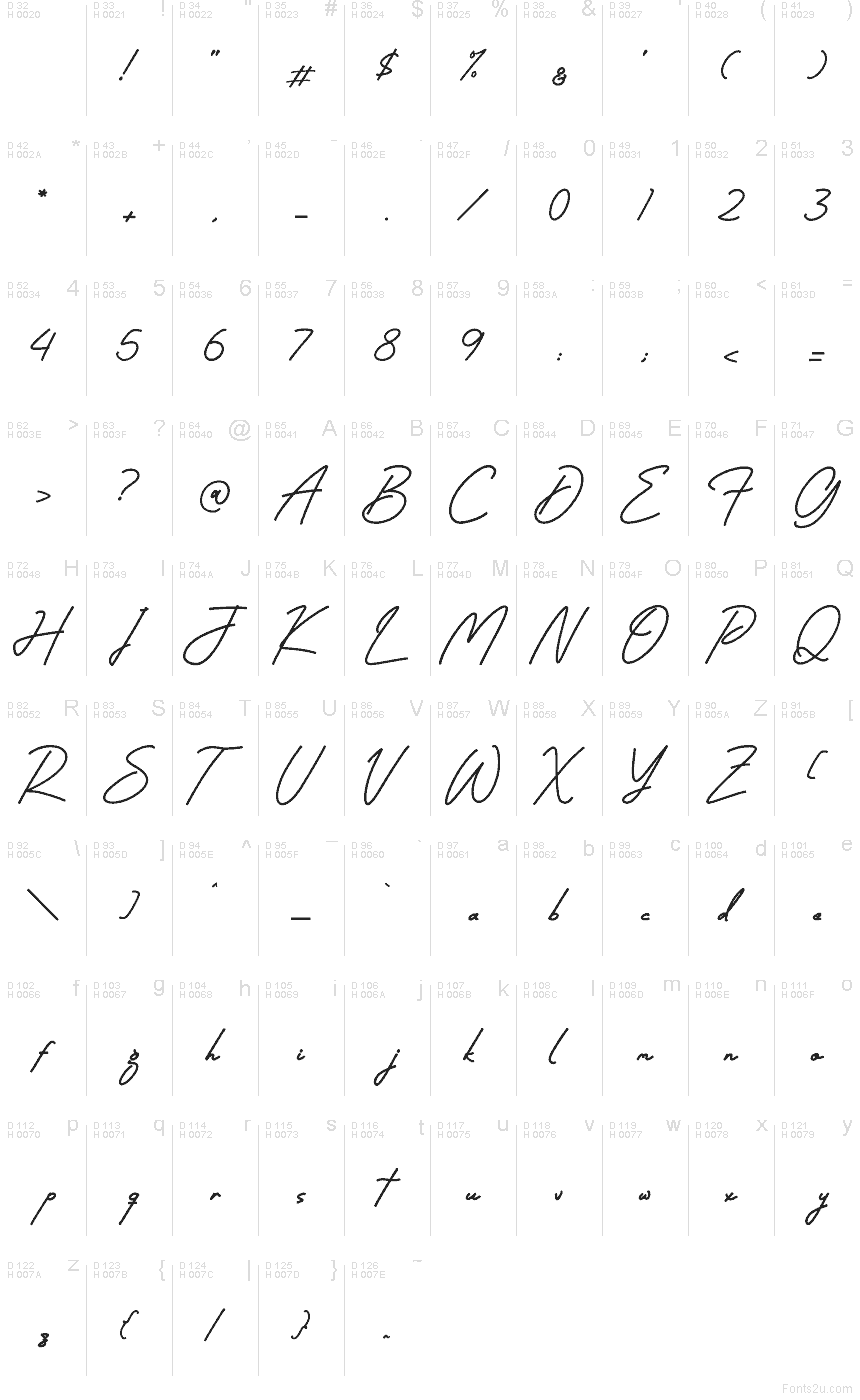
Floristone Phidelphia di Glorytype è un font calligrafico gratuito con un tratto leggero e alla moda. Le lettere si muovono con tratti lunghi e decisi, mescolando occhielli ariosi con raccordi rapidi e stretti: il risultato è un font che sembra un segno distintivo personale piuttosto che una scrittura troppo accurata.
È perfetto per il branding di boutique, packaging di fioristi, etichette di prodotti beauty, partecipazioni di nozze e header per i social media, dove quel tocco "firma" riesce a valorizzare il layout anche con poche parole. Essendo un font gratuito, è ideale anche per titoli, bozze di loghi e card che necessitano di un look moderno e delicato, senza risultare rigido o eccessivamente formale.